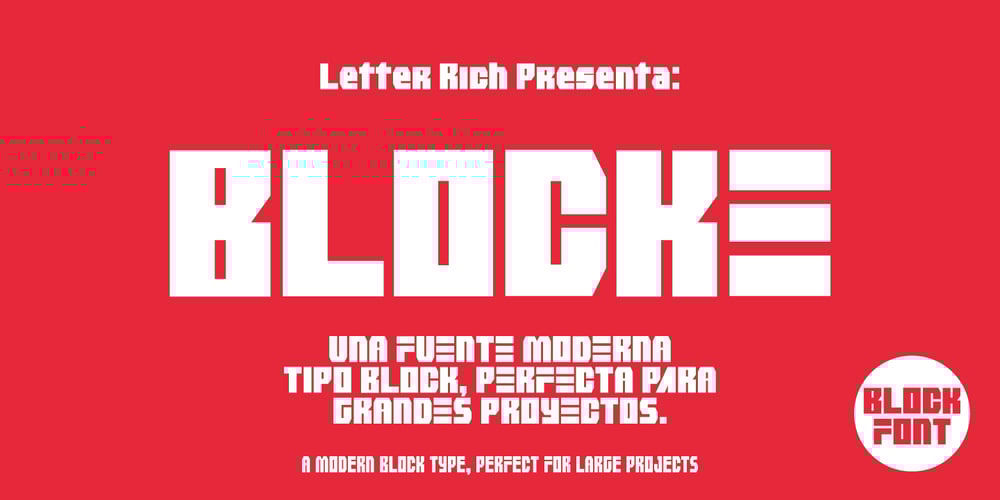
Blocke
Blocke font
Blocke Font Family was designed by Ricardo Patiño and published by RicardoLetters. Blocke contains 4 styles and family package options. Bloque es una fuente moderna de tipo bloque perfecta para proyectos de grandes dimensiones como vallas, pósters artísticos, señalización, packaging, títulos y logotipos. Ya que su contador es tan estrecho no debes usarla en tamaños pequeños porque la definición de cada carácter se perderá. Es una fuente que cuenta con una sensación limpia y minimalista. Bloque es una excelente elección cuando se necesita una fuente impactante de letras en bloque para crear diseños impresionantes.Bloque is a modern block font perfect for large projects like billboards, poster art, signage, packaging, headlines and logos. Since its counter is so narrow you should not use it in small sizes because the definition of each character will be lost. It’s a font that boasts a clean, minimalist feel. Bloque is an excellent choice when you need a striking font of block letters to create impressive designs.